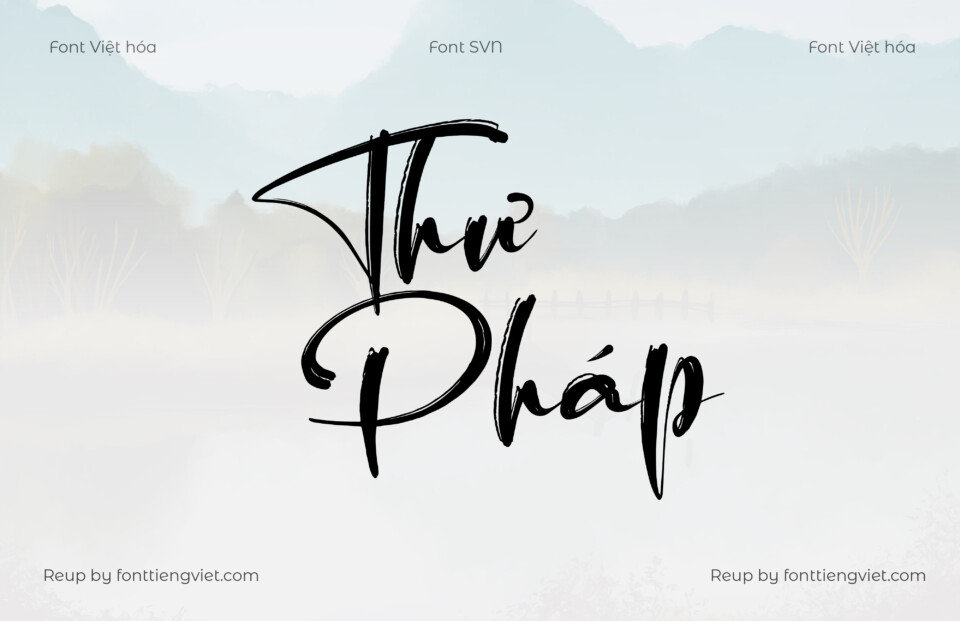
Tải Font Việt hóa SVN Hottroof Semhesta – Thư pháp – Brush Miễn Phí Cho Thiết Kế Ấn Tượng
Trong thế giới thiết kế đồ họa ngày càng phát triển, việc tìm kiếm một phong cách typography độc đáo, mang đậm dấu ấn cá nhân là điều cực kỳ quan trọng. Font Chữ không chỉ là công cụ truyền tải nội dung mà còn là linh hồn của tác phẩm. Hôm nay, chúng tôi hân hạnh giới thiệu đến bạn một tài nguyên quý giá: Font Việt hóa SVN Hottroof Semhesta – Thư pháp – Brush. Đây là một lựa chọn hoàn hảo cho những ai yêu thích phong cách viết tay (handwritten) phóng khoáng, nghệ thuật thư pháp (calligraphy) và các nét cọ (brush stroke) mạnh mẽ. Với khả năng hỗ trợ tiếng Việt đầy đủ, SVN Hottroof Semhesta chắc chắn sẽ nâng tầm các dự án sáng tạo của bạn, từ các ấn phẩm cá nhân cho đến các dự án thương mại chuyên nghiệp. Đây là một tài nguyên không thể thiếu đối với sinh viên, học sinh đang ôn thi tốt nghiệp muốn tạo ra các sản phẩm kỷ niệm ý nghĩa.
Khám Phá Chi Tiết về Phong Cách Nghệ Thuật của Font Việt hóa SVN Hottroof Semhesta – Thư pháp – Brush
SVN Hottroof Semhesta là một kiệt tác typography thuộc nhóm script font, được thiết kế để mô phỏng lại những nét viết tay dứt khoát, uyển chuyển của cọ vẽ. Sự kết hợp giữa nét chữ thư pháp cổ điển và cảm hứng brush hiện đại tạo nên một sự tương phản tuyệt vời, giúp font này nổi bật hơn hẳn các loại font viết tay thông thường. Phiên bản đã được Việt hóa hoàn chỉnh này giải quyết triệt để vấn đề lỗi font hoặc thiếu ký tự tiếng Việt, đặc biệt là các dấu thanh phức tạp, đảm bảo người dùng Việt Nam có thể sử dụng font một cách trơn tru và hiệu quả nhất trong mọi phần mềm thiết kế như Photoshop, Illustrator, hay Canva. Đặc trưng lớn nhất của nó là những đường cong mềm mại, các nét nối liền mạch và độ dày mỏng linh hoạt, truyền tải cảm xúc mạnh mẽ cho người xem. Đây là một tài sản không thể thiếu trong bộ sưu tập font chữ đẹp của bất kỳ nhà thiết kế đồ họa nào, đặc biệt khi cần tạo ra các ấn phẩm nghệ thuật cao.
Phong cách Thư pháp và Brush Hiện đại
Điều làm nên giá trị đặc biệt của SVN Hottroof Semhesta chính là sự giao thoa hài hòa giữa kỹ thuật thư pháp (calligraphy) truyền thống và phong cách brush (cọ vẽ) hiện đại, năng động. Các nét chữ như được vẽ bằng cọ thật, mang lại cảm giác chân thực, sống động. Khác với các font thư pháp quá nghiêm trang, SVN Hottroof Semhesta giữ lại sự trẻ trung, thích hợp cho các dự án hướng đến đối tượng học sinh, sinh viên, hoặc các ấn phẩm mang tính chất nghệ thuật đường phố. Sự tự do trong từng nét chữ thể hiện sự sáng tạo không giới hạn, rất phù hợp cho các thiết kế liên quan đến thiệp mời sự kiện, poster quảng cáo sản phẩm handmade, hay thậm chí là bìa sách cho các tác phẩm văn học nghệ thuật. Sự hỗ trợ Việt hóa giúp các câu quote hay thông điệp tiếng Việt trở nên hoàn hảo, không bị mất đi vẻ đẹp tự nhiên của font gốc.
Ứng Dụng Sáng Tạo của Font SVN Hottroof Semhesta trong Thiết Kế Đồ Họa
Với vẻ ngoài độc đáo và tính năng Việt hóa hoàn hảo, font SVN Hottroof Semhesta mở ra vô vàn cơ hội ứng dụng trong nhiều lĩnh vực khác nhau. Từ truyền thông số đến in ấn vật lý, font này luôn biết cách tạo điểm nhấn mạnh mẽ. Đặc biệt, đối với các trường học, cơ sở giáo dục hoặc các sự kiện liên quan đến học tập và thi cử, việc sử dụng một font chữ nghệ thuật có thể làm tăng tính trang trọng và hấp dẫn cho thông điệp truyền tải. Ví dụ như trong việc thiết kế bằng khen, giấy chứng nhận hoặc các ấn phẩm kỷ yếu, nơi cần sự kết hợp giữa nét cá nhân và sự chuyên nghiệp.
Thiết kế Logo và Nhận diện Thương hiệu
Font SVN Hottroof Semhesta rất lý tưởng để tạo ra các logo mang tính cá nhân hóa cao. Các thương hiệu về thời trang, ẩm thực, mỹ phẩm handmade hay studio nghệ thuật thường ưu tiên sử dụng font này để thể hiện sự tinh tế, thủ công và độc quyền. Nhờ vào các ký tự đặc biệt và đường nét uyển chuyển, logo của bạn sẽ tránh được sự nhàm chán, tạo ấn tượng sâu sắc ngay từ cái nhìn đầu tiên. Việc này rất quan trọng trong môi trường cạnh tranh khốc liệt của thị trường hiện nay, giúp doanh nghiệp dễ dàng khắc sâu hình ảnh vào tâm trí khách hàng mục tiêu. Font chữ này mang lại cảm giác sang trọng nhưng không quá cứng nhắc, rất linh hoạt trong phối màu và bố cục.
Thiết kế Ấn phẩm Học đường và Sự kiện Tốt nghiệp Trung học
Đối với các bạn học sinh, sinh viên chuẩn bị cho lễ tốt nghiệp hoặc các kỳ thi quan trọng như kỳ thi tốt nghiệp trung học phổ thông, việc tạo ra những kỷ vật đẹp là điều không thể thiếu. Font SVN Hottroof Semhesta có thể được dùng để thiết kế thiệp mời dự lễ tốt nghiệp, tiêu đề cho kỷ yếu cuối khóa, hoặc thậm chí là trang trí các bản tóm tắt ôn tập. Sự mềm mại nhưng dứt khoát của font chữ này tạo nên sự cân bằng hoàn hảo giữa tính trang trọng của sự kiện và sự trẻ trung của thế hệ học sinh. Nó làm nổi bật các thông điệp chúc mừng và cảm ơn một cách đầy cảm xúc, giúp lưu giữ những khoảnh khắc đáng nhớ trong đời học sinh.
Tóm lại, Font Việt hóa SVN Hottroof Semhesta – Thư pháp – Brush là một tài sản vô giá đối với bất kỳ ai đang tìm kiếm sự khác biệt và chất nghệ thuật trong các dự án typography của mình. Từ việc tạo ấn phẩm cho sinh viên, thiết kế kỷ yếu tốt nghiệp, cho đến việc xây dựng nhận diện thương hiệu chuyên nghiệp, font chữ này đều mang lại hiệu quả thị giác vượt trội. Đừng ngần ngại bổ sung ngay font chữ độc đáo này vào bộ sưu tập của bạn để khám phá tiềm năng sáng tạo không giới hạn. Việc lựa chọn Font Chữ phù hợp chính là bước đầu tiên để tạo ra một tác phẩm đáng nhớ và thu hút. Hãy tải ngay hôm nay và bắt đầu hành trình thiết kế đầy cảm hứng!